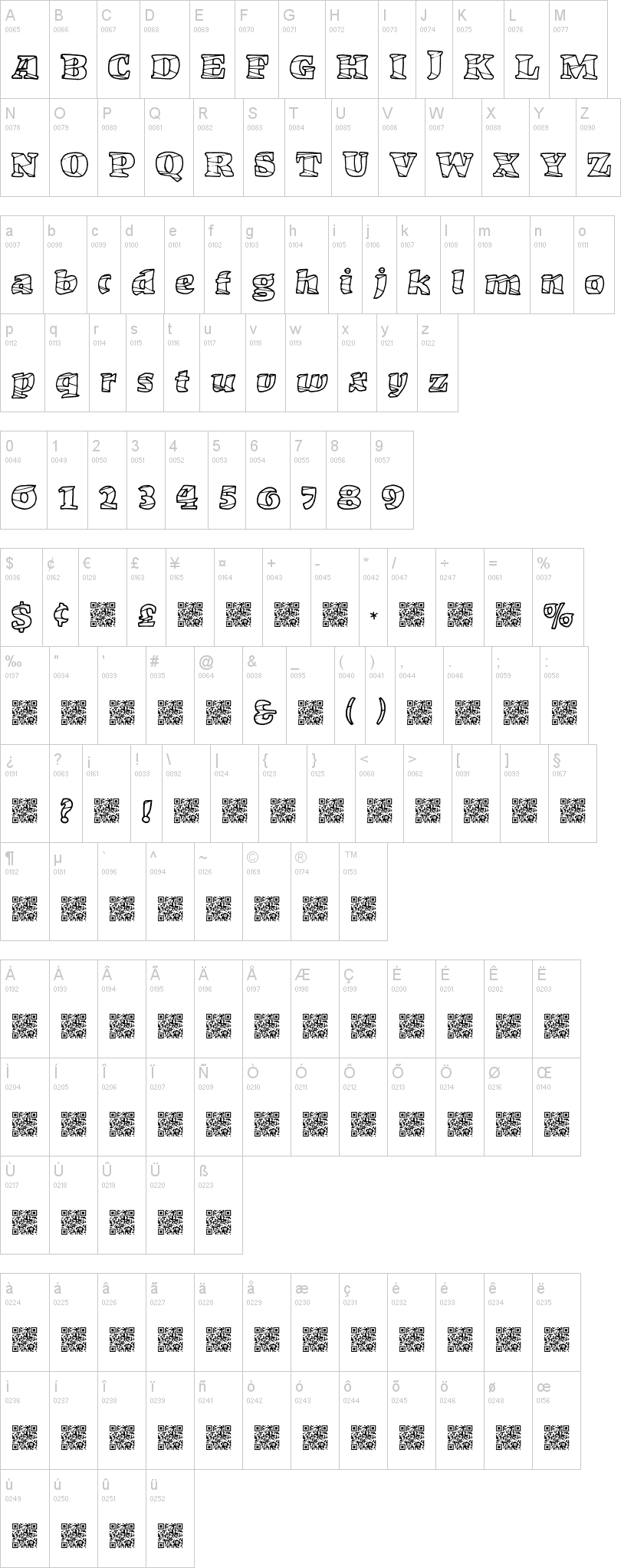
Market Crash
Market Crash 字体是一款非常具有特色的字体,常用于各种商业和金融相关的设计中。它的特点是字体笔画较为粗犷,线条硬朗,给人一种坚毅、稳健的感觉。同时,字体中的每个字母都带有一些仿佛是错位或抖动的元素,让整个字体看起来更加生动、有力量感。这种字体常用于海报、广告、标志、书籍封面等设计中,特别是一些需要强调稳定性和可靠性的场合。
Market Crash是一款非常不错的手写艺术字体,具有很好的视觉感,适合于文化类的宣传设计、商业类品牌的广告和产品包装设计以及个性化文字排版等较多场景。